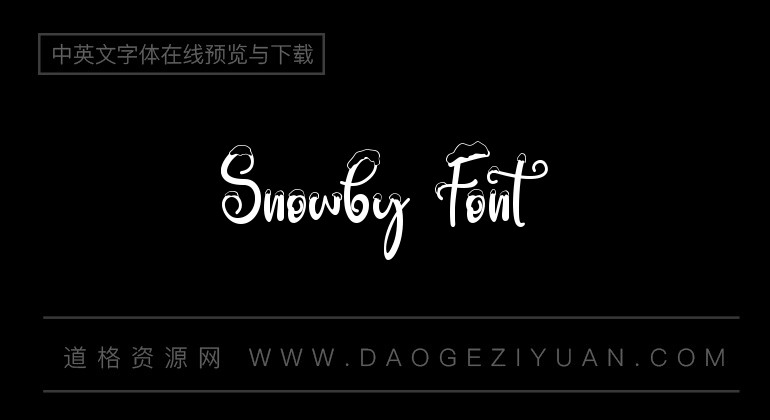
Snowby Font
Snowby Font 是一种英文字体,特点是字母看起来像是被雪覆盖的,因此得名 Snowby。它的字母边缘带有细小的锯齿状花纹,使得整体效果非常有趣和独特。 这种字体适合用于一些寒冷、清新的场合,比如冬季主题的海报、广告、贺卡等等。使用 Snowby Font 可以营造出一种轻松、愉悦的氛围,也可以加强设计主题的整体感觉。 Snowby Font 目前可在多个字体网站上免费下载,也有付费版本提供更多的特色字体。
Snowby Font是一款非常不错的手写艺术字体,具有很好的视觉感,适合于文化类的宣传设计、商业类品牌的广告和产品包装设计以及个性化文字排版等较多场景。